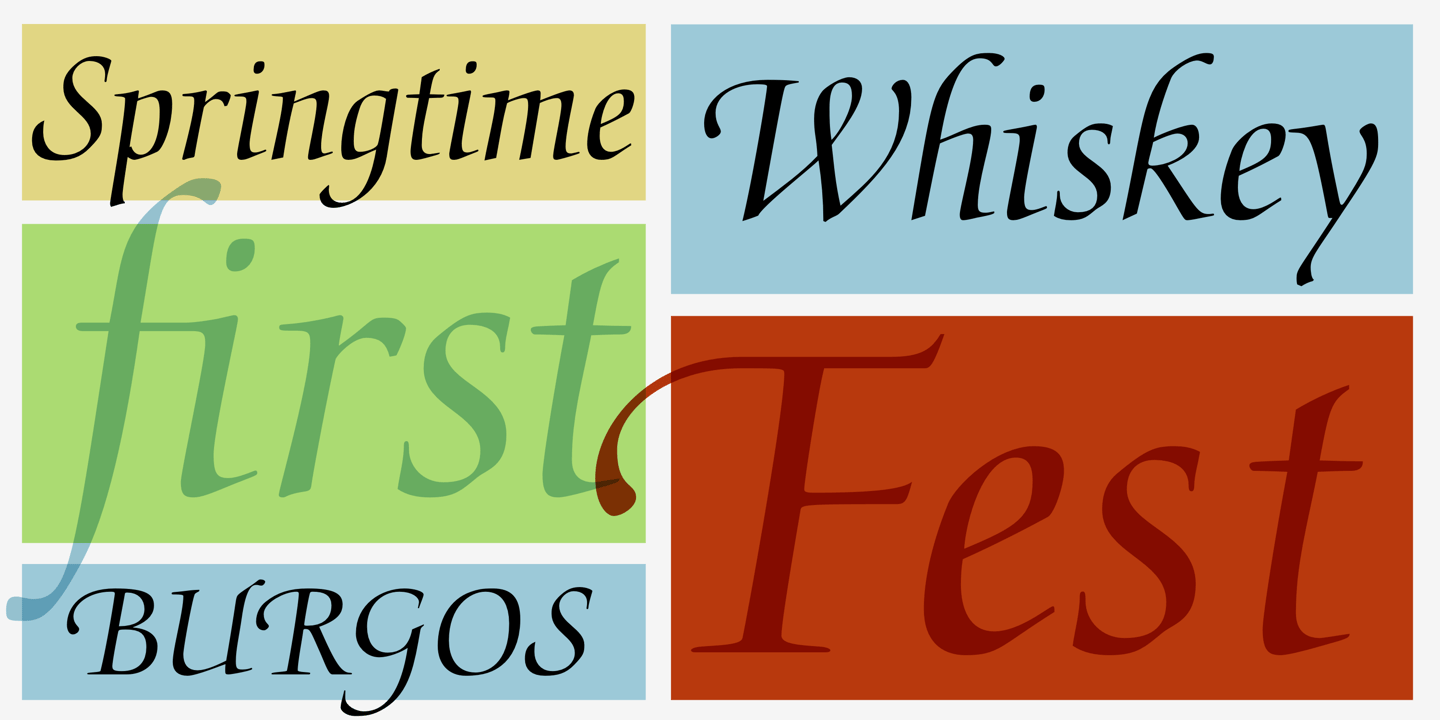
• 1971
• Antiqua Schreibschrift
Die Medici Script ist eine unverbundene Schreibschrift von Hermann Zapf und erschien 1971 als Fotosatzschrift bei Linotype in einem Schnitt.